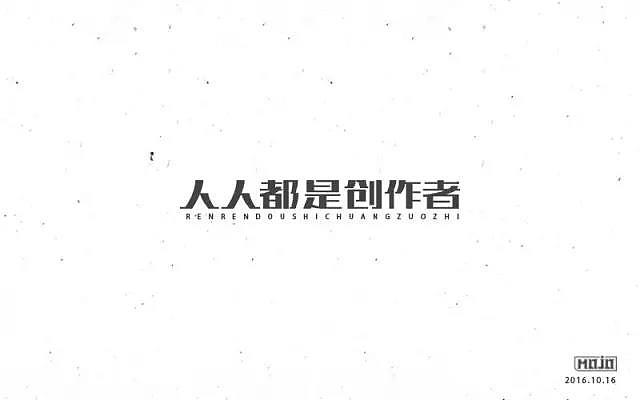
字体帮20161016期点评作品
写的蛮卡通,蛮好玩,但把AI和PS加在里边,就显得比较狭隘了,创意的选择很是重要,我们可以随便想到很多与创作相关的元素或图形,但必须要经历筛选的过程,像灯泡、铅笔、鼠标等元素,其涵义就会更广泛,更有行业代表性,所以说,希望大家在想创意的时候,不要着急去画,再多想一想……
这个字体确实没什么大问题,但做的没有太多创意和亮点,既然这七个字是与创作相关,与设计相关,与站酷网相关,就应该从设计师的角度出发,要做的好玩、有趣、至少设计师会喜欢才行……
我不谈这个字形做的好坏,就只抓一个问题:做错字了,创作者,而不是创造者,在投稿作品里,至少有五六份作品都出现了这样的低级失误,请自己躲在角落反省一下………………
而上面的三例,出现的问题比较一致,是字体组合和排序上不太恰当,不方便阅读,字体比较多的时候,这个问题也是很容易出错的,需要多多谨慎……